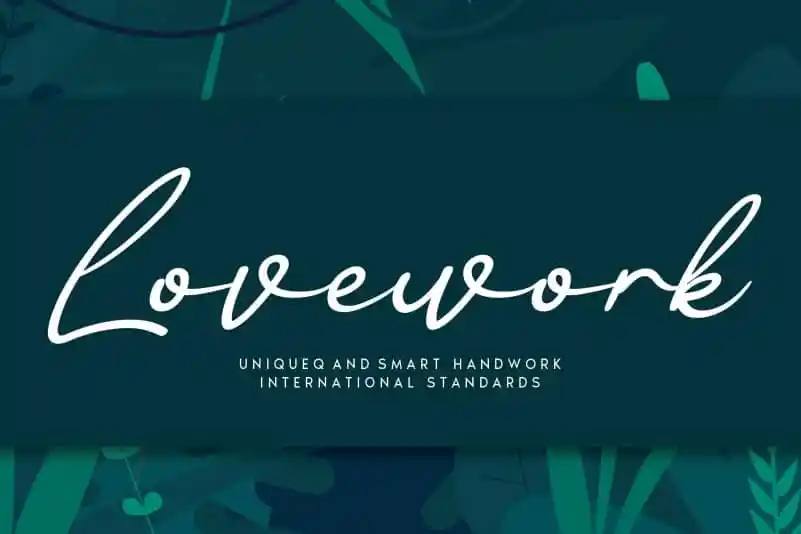
Lovework Handwritten Font – Download Grátis
A fonte Lovework Handwritten é uma criação única ideal para designers que desejam um toque pessoal em suas criações digitais. Este produto oferece uma experiência especial, com traços suaves e autênticos que trazem à vida a sua arte digital. Sujeitada ao estilo de escrita casual e confiante do designer, esta fonte irá adicionar um toque amigável às suas mensagens digitais ou trabalhos gráficos. Crie designs semelhantes aos encontrados em cartões-postais ou textos pessoais, mas com o poder de uma ferramenta digital. Composta por traços elegantes e detalhes cuidadosamente gerenciados, Lovework Handwritten é perfeita para criar mensagens amigáveis que despertam a empatia e transmitem um sentimento único, tornando sua marca mais pessoal e reconhecível. Esta fonte está aqui para ajudar você a expressar-se de forma única e poderosa no mundo digital.